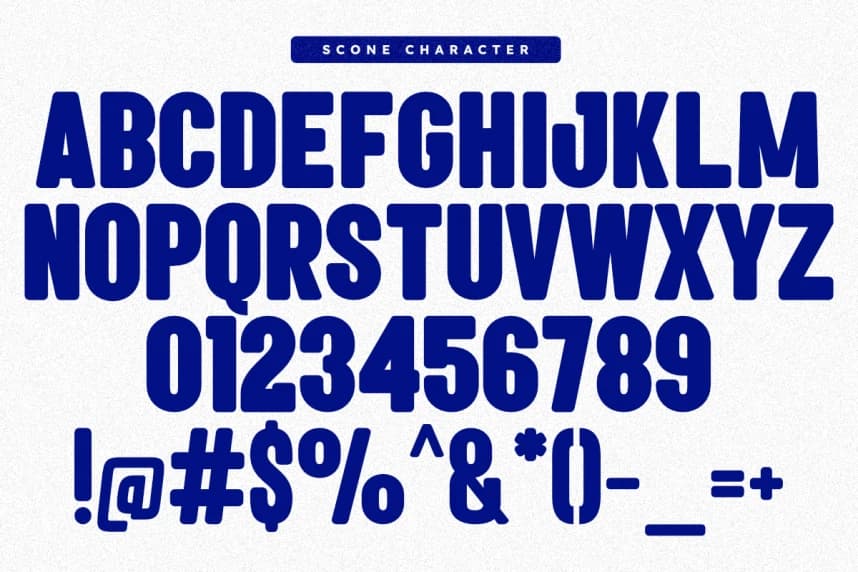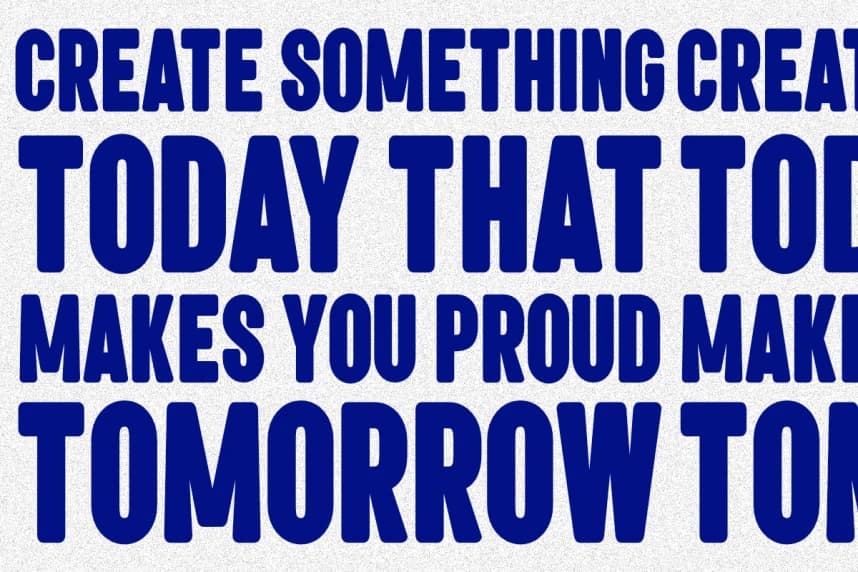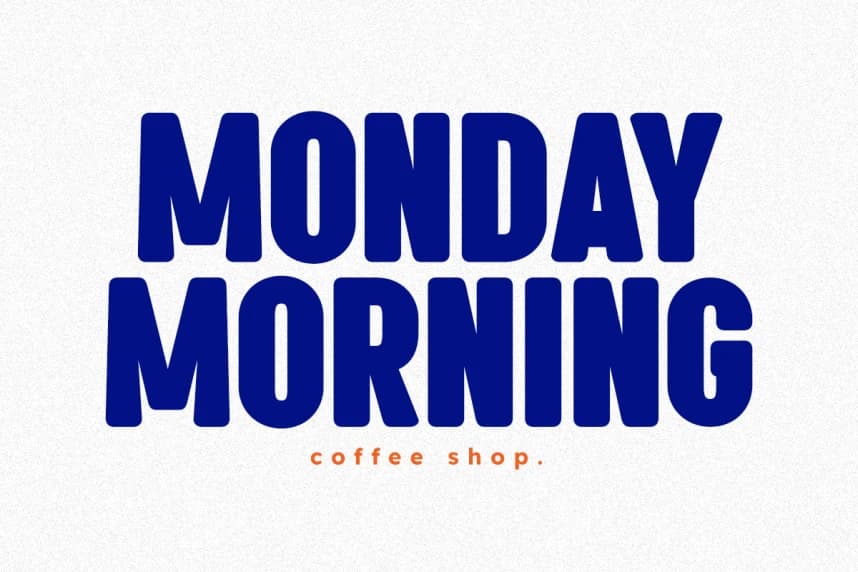
Scone Font
Scone Font, modern yaratıcı projelerinize hoş bir vintage sıcaklığı ve göz alıcı estetik kazandırmak için özenle seçilmiş, kalın, retro, sıkıştırılmış sans serif yazı tipidir. Güçlü, sıkıştırılmış yapısal anatomisi ve dostça yuvarlak geometrik konturlarıyla öne çıkar.
Scone Font kalın retro sıkıştırılmış sans serif bir font olup modern yaratıcı projelerinize hoş bir vintage sıcaklığı ve dikkat çekici estetik katmak için özenle seçilmiştir. Güçlü, sıkıştırılmış yapısal anatomisi ve dostça yuvarlak geometrik konturlarıyla dikkat çeker.